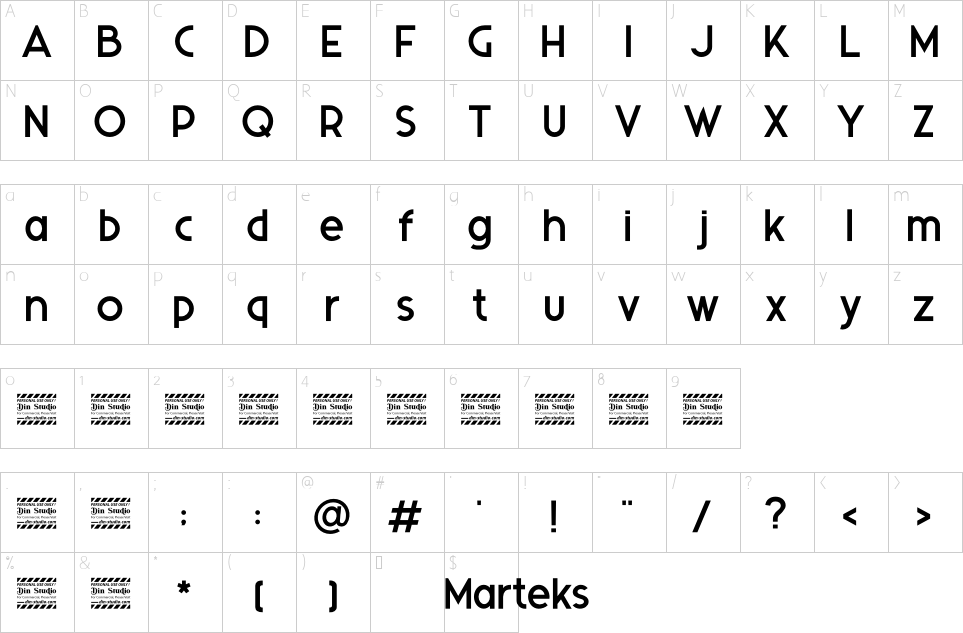
Marteks é uma fonte de estilo moderno e clean que combina elegância com simplicidade. Ela foi criada pelo Din Studio e tem sido popular por sua capacidade de criar textos profissionais e sofisticados. Com um design leve e harmonioso, Marteks é uma opção ideal para designers que buscam um equilíbrio entre modernidade e estilização. A fonte é fácil de se adaptar a diversos estilos, adequando-se tanto para rótulos profissionais quanto para editoriais e textos mais livres. Marteks é perfeita para ambientes de trabalho modernos e para aqueles que buscam um recurso gráfico elegante e versátil. Com seu design limpo e sofisticado, a Marteks está disponível gratuitamente tanto para sistemas Windows quanto para Mac.